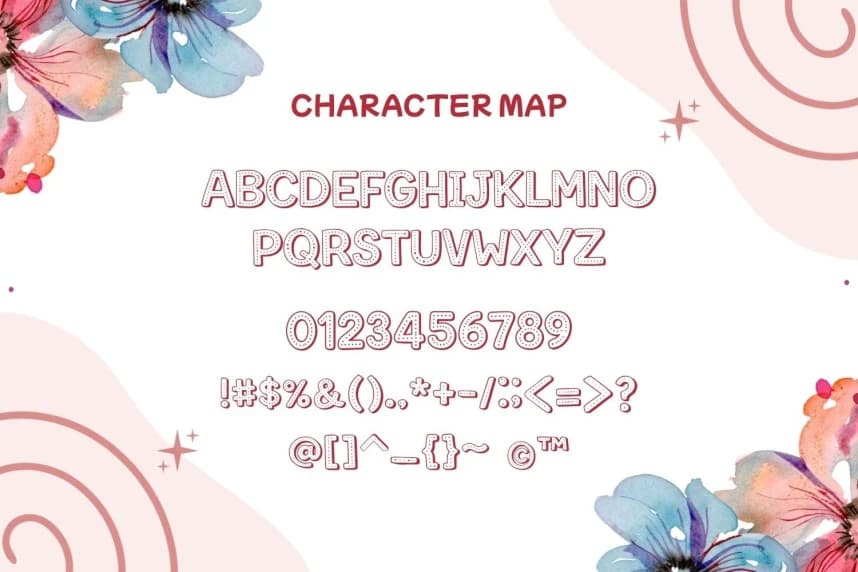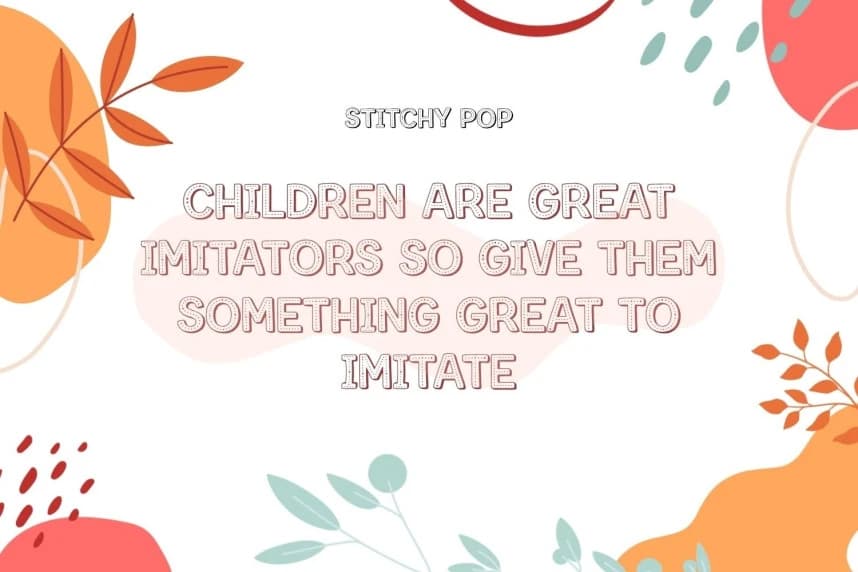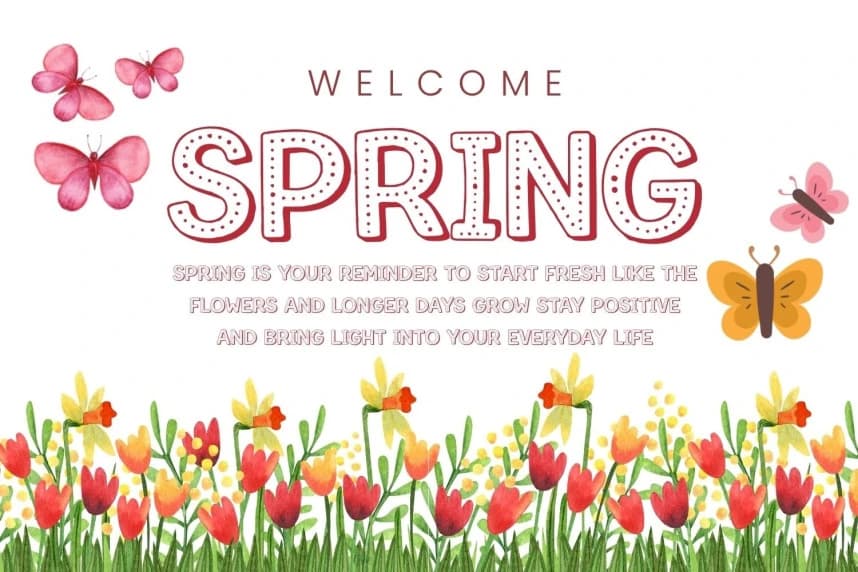
Stitchy Pop Font
Stitchy Pop Font, yumuşak, eğlenceli ve beğenilmesi kolay görünen bir font. Harfler dostça bir his veriyor ve biraz da oyunbaz, bu yüzden her kelime güzel ve davetkâr görünüyor. Nazik bir stile sahip olan bu font, okumayı sakin ve mutlu hissettirir.
Stitchy Pop Font yumuşak, eğlenceli ve beğenilmesi kolay görünen bir fonttur. Harfler arkadaşça ve biraz oyuncu hissi veriyor, bu yüzden her kelime hoş ve davetkar görünüyor. Okumayı sakin ve mutlu hissettiren nazik bir stile sahip.
Stitchy Pop
Stitchy Pop Regular